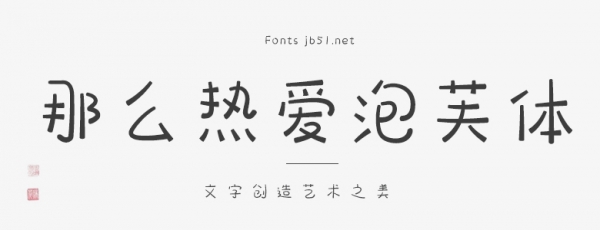
那么熱愛(ài)泡芙體是那么熱愛(ài)造字推出的一款呆萌藝術(shù)字體,字跡工整,舒適易讀,簡(jiǎn)約可愛(ài)又不失恬適美好,字跡工整,清新甜美,給人以簡(jiǎn)單舒適的感覺(jué),適用于包裝設(shè)計(jì)、電商、品牌名稱(chēng)、漫畫(huà)、影視綜藝、游戲、各類(lèi)商業(yè)海報(bào)、戶外廣告標(biāo)題等設(shè)計(jì)領(lǐng)域,歡迎喜歡此字體的朋友前來(lái)下載使用。